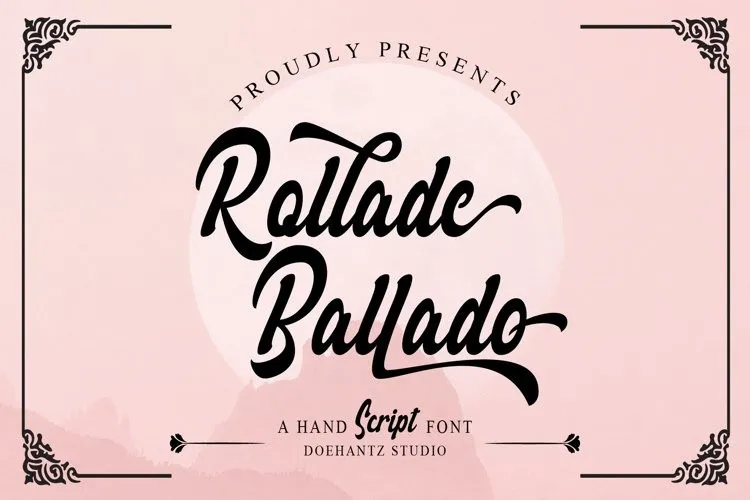
Rollade Ballado Font – Download Grátis
A fonte Rollade Ballado foi criada por Doehantz Studio inspirada nas estilos retro e na arquitetura artística de postais antigos e sinais. Suas linhas elegantes e sofisticadas se destacam em diversos projetos de design, desde marcas de produtos e cartões de visitas até selos casamento e assinaturas. Esta font possui uma variedade imensa de alternativas de caracteres que certamente aprimoram qualquer projeto gráfico, oferecendo tanto flexibilidade quanto beleza única. Seja você um artista digital ou designer gráfico, Rollade Ballado é uma escolha segura para criar designs que se destacam. Compre agora e adicione elegância e originalidade ao seu próximo design!